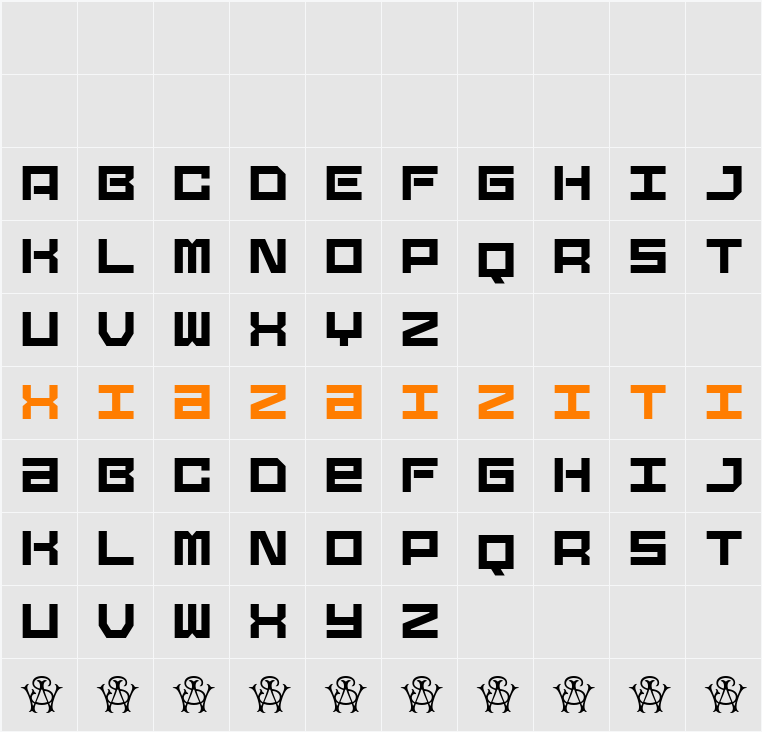
WS Bind
WS Bind,这款字体结构工整、笔画清晰,兼顾美观与易读性,适用于标题、正文、海报、包装、LOGO 等多种场景。字形优雅稳定,风格百搭耐看,适配日常排版与创意设计,让文字呈现更舒适、更具质感。WS Bind一笔一画,皆是细节,以均衡的比例、流畅的线条打造舒适视觉体验,字形端正大气,风格简约现代。无论是商业设计、品牌宣传还是日常排版,都能轻松驾驭,让文字更有格调与力量。WS Bind字体下载。